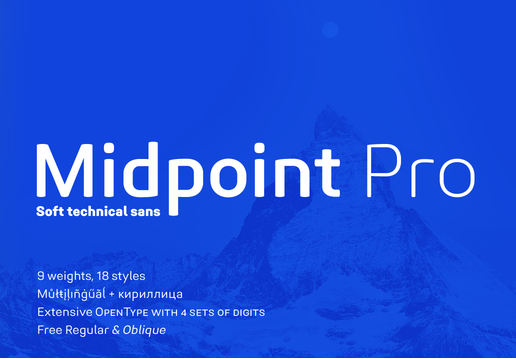
Midpoint Pro Font Family – Fonte Grátis
Midpoint Pro Font Family
Introduzimos a nova família de tipos de letra Midpoint Pro Font Family, criada pelo Mint Type. Midpoint Pro é uma tipografia sans-serif suave que apresenta um olhar técnico moderno. Seu design sem aparentes curvaturas cria um equilíbrio perfeito entre as verticals estáticas e rígidas e os encerramentos acolhidos, resultando num impactante contraste visual. O jogo entre formas abertas e fechadas sugere uma legibilidade aprimorada em tamanhos menores, dando ao texto um delicado toque de textura vibrante. Midpoint Pro é perfeito para estilos contemporâneos que valorizam uma mistura elegante de severidade e suavidade.